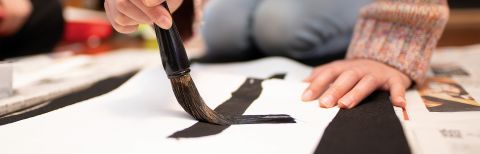
Der Wert von Schrift und Schriftkunst
Schreiben mit der Hand ist wichtig für die menschliche Entwicklung. Das ist das Thema des Tags der Handschrift und auch ein roter Faden, der sich durch die Bildung in Ostasien zieht. In China galt die Kunst des Schreibens mit der Hand als höchste menschliche Entwicklung: eine Kunstform, die alle anderen Künste, wie Malerei oder Bildhauerei, übertraf. Dabei ging es nicht darum, eine „schöne Schrift“ zu schaffen, sondern einen Stil zu entwickeln, der die Persönlichkeit des Schreibers widerspiegelt. Man glaubte, je stärker die Persönlichkeit, desto bemerkenswerter die Handschrift. Selbst Fehler und gelöschte Abschnitte wurden als Zeichen spontaner Kreativität gesehen. Es gibt wichtige Parallelen zum vorliegenden Buch: das heißt, Handschrift muss nicht den Schönheitsstandards eines Lehrbuchs entsprechen – sie muss vielmehr der persönliche Ausdruck der oder des Schreibenden sein und eine ausgeprägte Persönlichkeit hinter der Feder zeigen. Und wichtig ist, dass – wie die alten Chinesen betonten – der persönliche Stil nur durch wiederholtes Schreiben entwickelt werden kann. Wichtig ist nicht nur, was geschrieben wird, sondern auch, wie es geschrieben wird.
Mit dem Aufkommen von Computern, Smartphones und anderen elektronischen Hilfsmitteln, die das Schreiben für uns übernehmen, ist die Kunst des Schreibens mit der Hand im Niedergang begriffen. Das gilt sowohl im Westen als auch im Osten. Dennoch gibt es keinen Grund zur Verzweiflung. Die Handschrift mit dem Pinsel wird zum Beispiel noch in japanischen Grundschulen gelehrt, und Wettbewerbe und Ausstellungen dazu sind in allen drei großen ostasiatischen Kulturen immer noch an der Tagesordnung. Im Mittelpunkt stehen nach wie vor Pinsel, Tinte und Papier: Die Formate, Stile und die Werkzeuge, selbst die koordinierten Bewegungen von Arm, Handgelenk und Hand haben sich über die vielen Jahrhunderte nicht wesentlich verändert.
Während die jungen ostasiatischen Tintenschreibschülerinnen und -schüler sich auf eine 2.000 Jahre alte Tradition stützen und sich von ihr inspirieren lassen können, gibt es auch einen erheblichen Nachteil: Von einem funktionstüchtigen Erwachsenen wird erwartet, dass er in Japan über dreitausend und in China
vier- bis fünftausend Schriftzeichen kennt. Wenn wir das mit unseren 26 Buchstaben vergleichen, können wir die Schwierigkeiten ostasiatischer Schülerinnen und Schüler erahnen. Dennoch zeigt dies die Wichtigkeit: dass trotz solch erheblicher Hindernisse immer noch großer Wert auf das Erlernen des Schreibens mit der Hand gelegt wird. Davon können wir im Westen sicherlich lernen, wenn wir darüber nachdenken, wie wir Kinder zu denkenden, aktiven Mitgliedern der Gesellschaft erziehen können.
Der Tag der Handschrift versucht, wie unsere ostasiatischen Kolleginnen und Kollegen, den Schwerpunkt wieder auf die alten Fähigkeiten des Schreibens mit der Hand zu legen, auch in einer Welt, die von modernen technischen Innovationen umgeben ist.